Guys saya tau bahwa font itu preferensi masing-masing🙂. Tapi mau nanya aja sih, barangkali mau sharing juga,
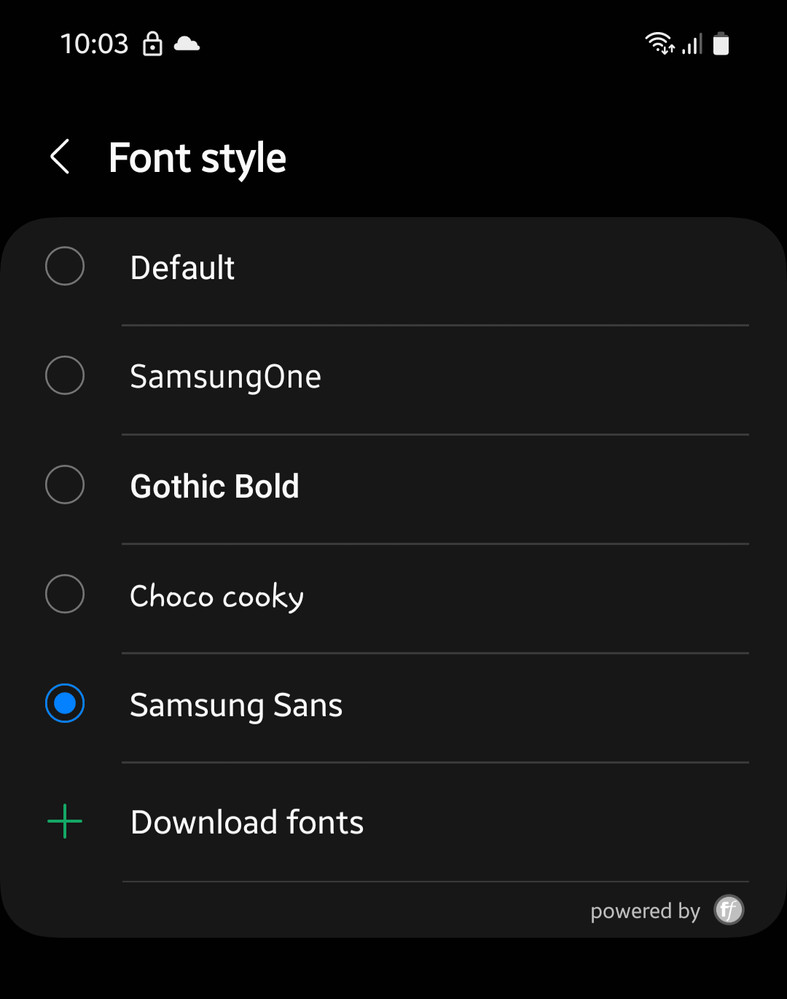
Font yang saya gunakan
Sekarang para samsung member sekalian pada pakai jenis font apa yaa di Handphone samsungnya? Mungkin ada alasannya juga kenapa pake font tersebut hehe
Saya sendiri pakaiSamsungSans, kenapa?
Menurut saya fontnya lebih ikonik samsung aja, lebih fresh dari font bawaan atau defaultnya, dannn gratiss 😭 hehe✌🏼